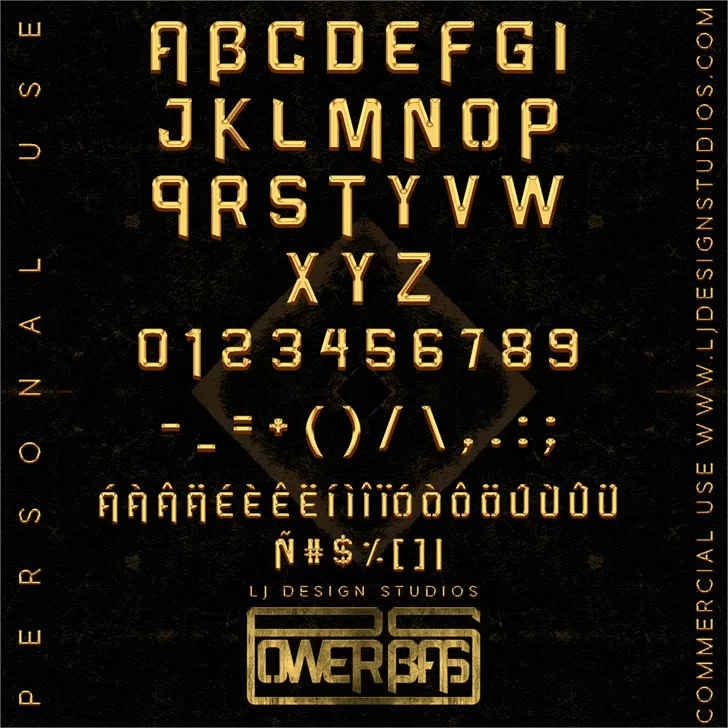
A Power Bass é uma exuberante e vibrante fonte display desenvolvida por Hamilton que se destaca nas páginas mais visíveis dos sites e aplicativos. Esta fonte traz um toque de adrenalina à sua identidade visual, com traços robustos e linhas fortes que chamam a atenção do público. Seu design elegante combina bem em diversas aplicações como websites, logomarcas ou materiais publicitários, proporcionando uma presença assertiva e moderna. Para acessar versões comerciais disponíveis para uso comercial, visite o site http://ljdesignstudios.es.tl/Power-Bass.htm ou entre em contato direto por e-mail a . Seja qual for seu projeto visual, a Power Bass é certamente um acréscimo incrível à sua paleta de fontes.